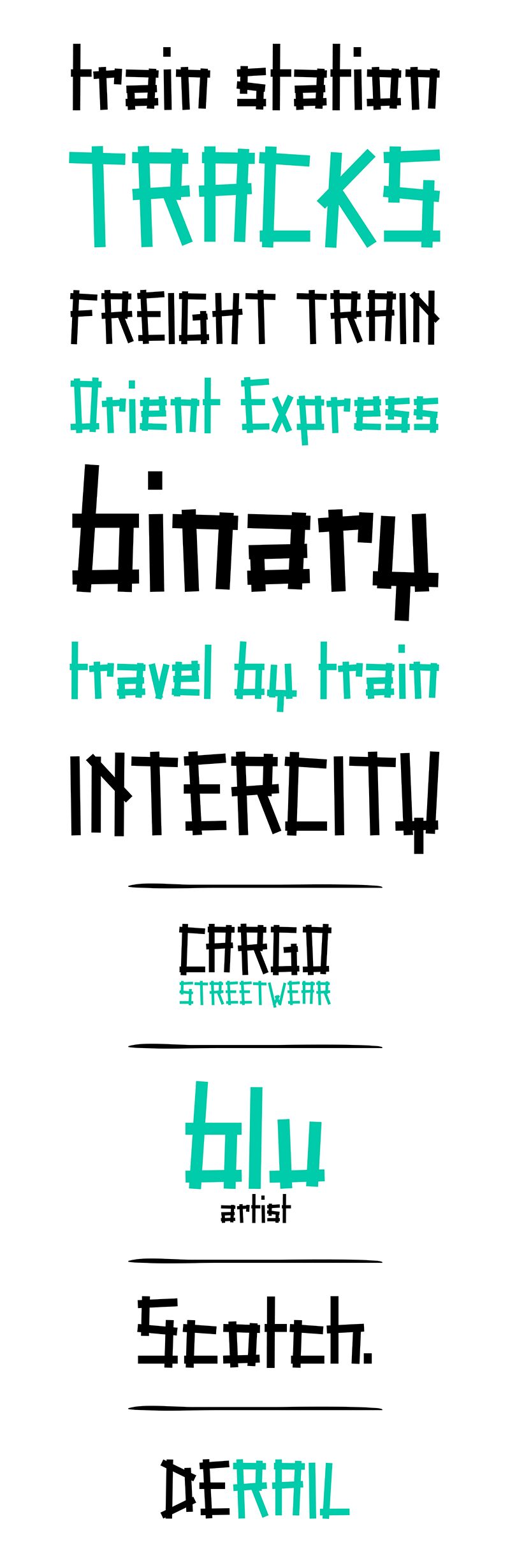
Tape Rail, zaprojektowany przez Katiuscię Mari dla Monocromo, to dynamiczny i zabawny font typu display, który dzięki swojej półlekkiej wadze i skondensowanej formie nabiera niemal rysunkowego charakteru. Dzięki odręcznemu stylowi Tape Rail ucieleśnia swobodną, a zarazem wyrazistą estetykę, która natychmiastowo dodaje każdemu projektowi radości i kreatywności. Stylizowany wygląd sprawia, że jest to doskonały wybór do nagłówków, logotypów i wszelkich prac projektowych, w których liczy się osobowość.
Niezależnie od tego, czy tworzysz przyciągające wzrok plakaty, czy odświeżasz stronę internetową, unikalne połączenie fantazji i śmiałości Tape Rail z pewnością pobudzi wyobraźnię Twoich odbiorców.